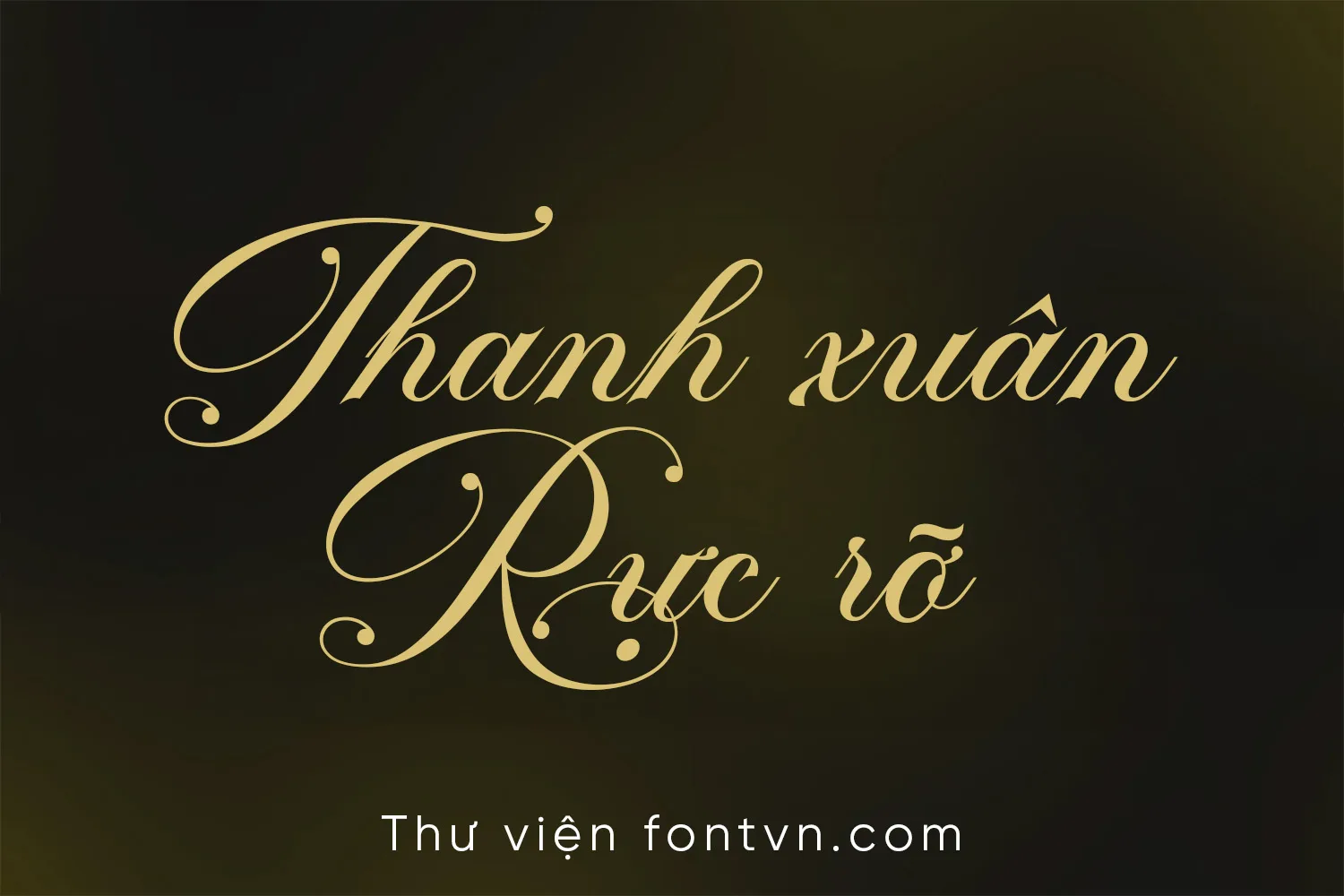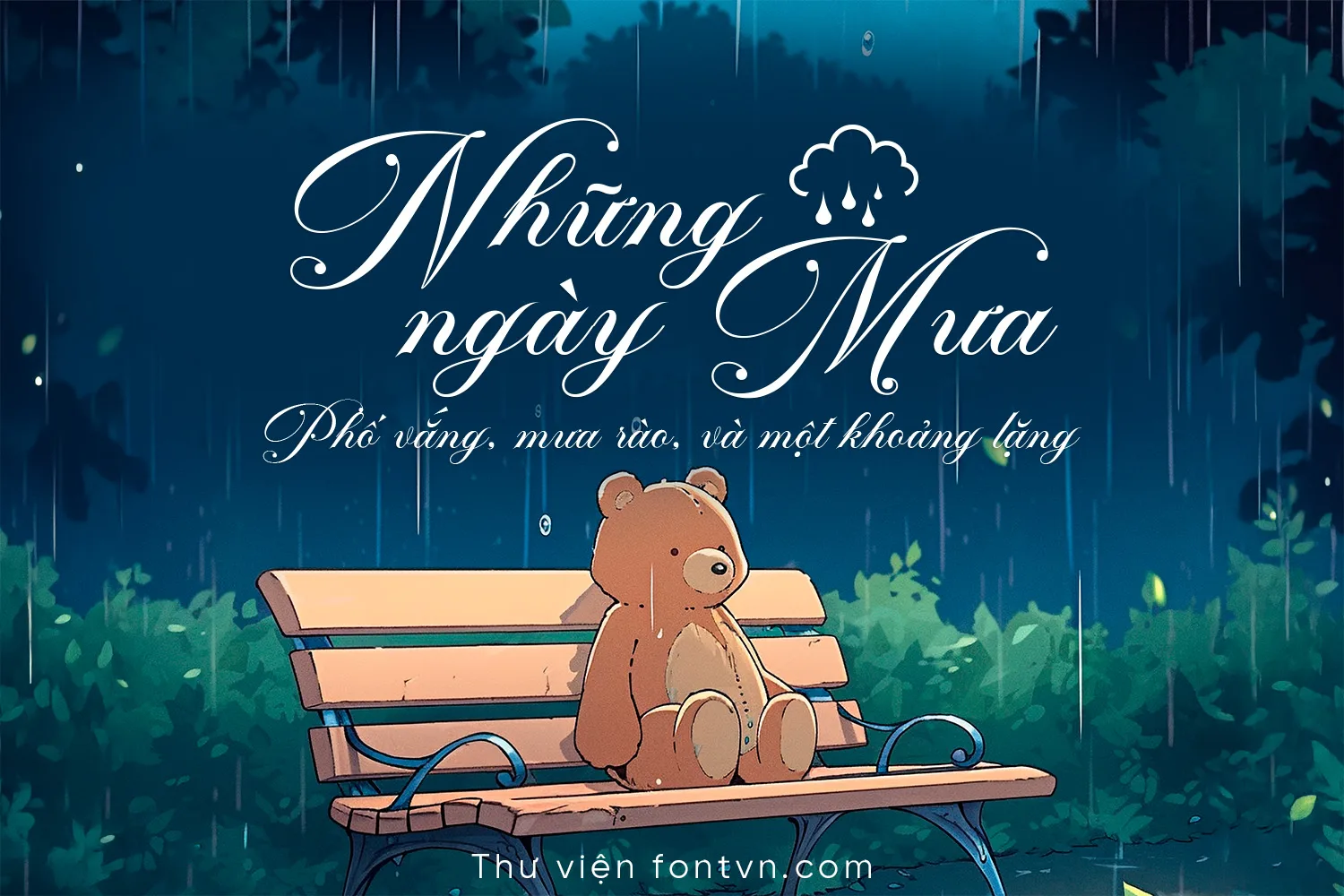
DVN Poema Script tiếng Việt – Font Chữ Ký Sang Trọng Cho Thiệp Cưới
DVN Poema là một phông chữ script mang phong cách Calligraphy cổ điển, nổi bật với độ tương phản nét thanh – nét đậm sắc nét và các đường nét uốn lượn (swash) tinh xảo. Cấu trúc chữ được thiết kế tỉ mỉ với trục nghiêng đồng nhất, giúp các ký tự kết nối liền mạch và tạo ra một tổng thể thị giác sang trọng, chuyên nghiệp.
Thiệp mời sự kiện, thiệp cưới (Wedding invitations).
Thiết kế Logo/Nhận diện thương hiệu phân khúc cao cấp (Trang sức, Mỹ phẩm, Thời trang, Spa).
Bao bì sản phẩm mang phong cách vintage/classic.
Các đoạn tiêu đề ngắn (Headings, Display Text) cần tạo điểm nhấn.